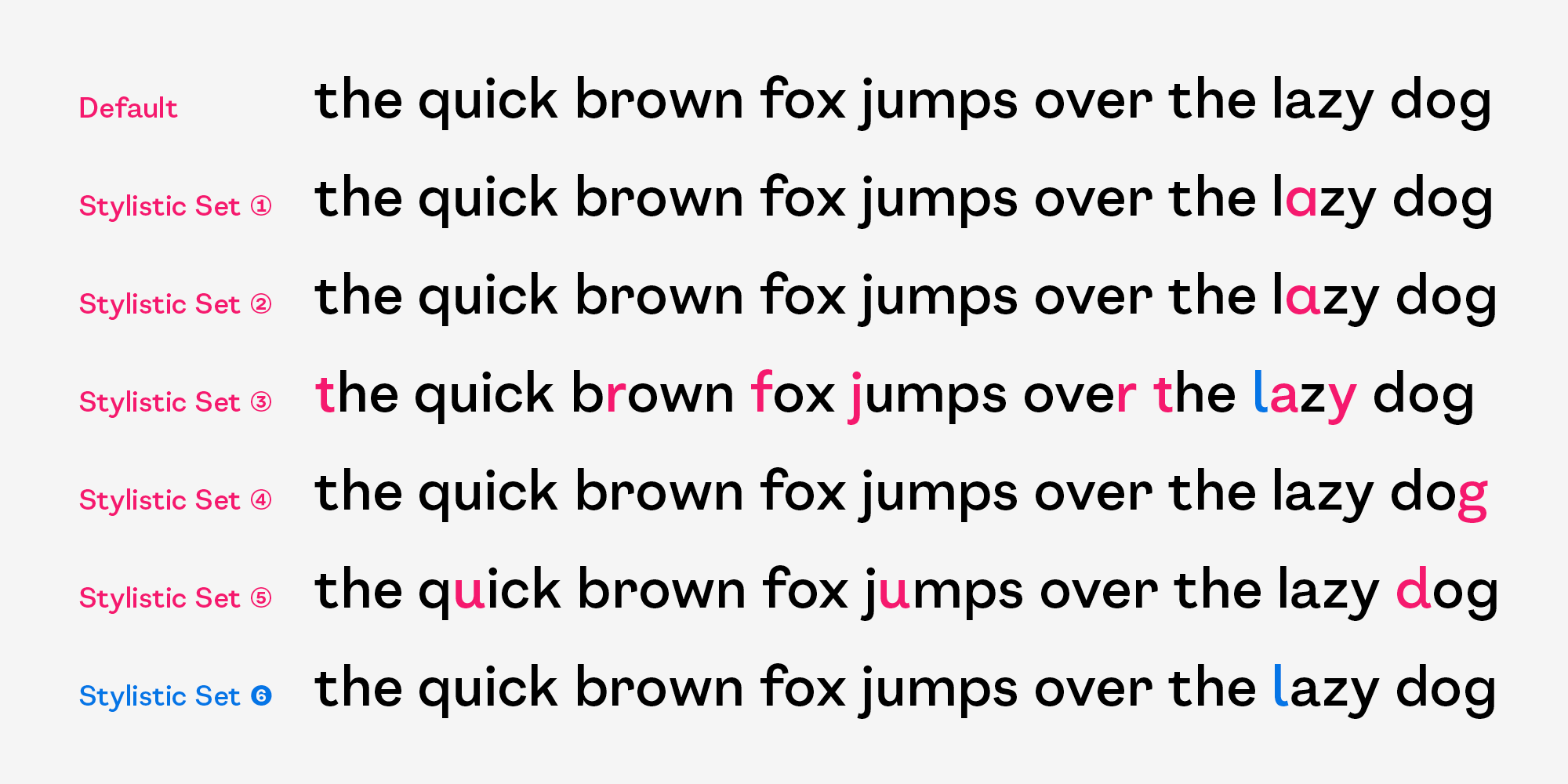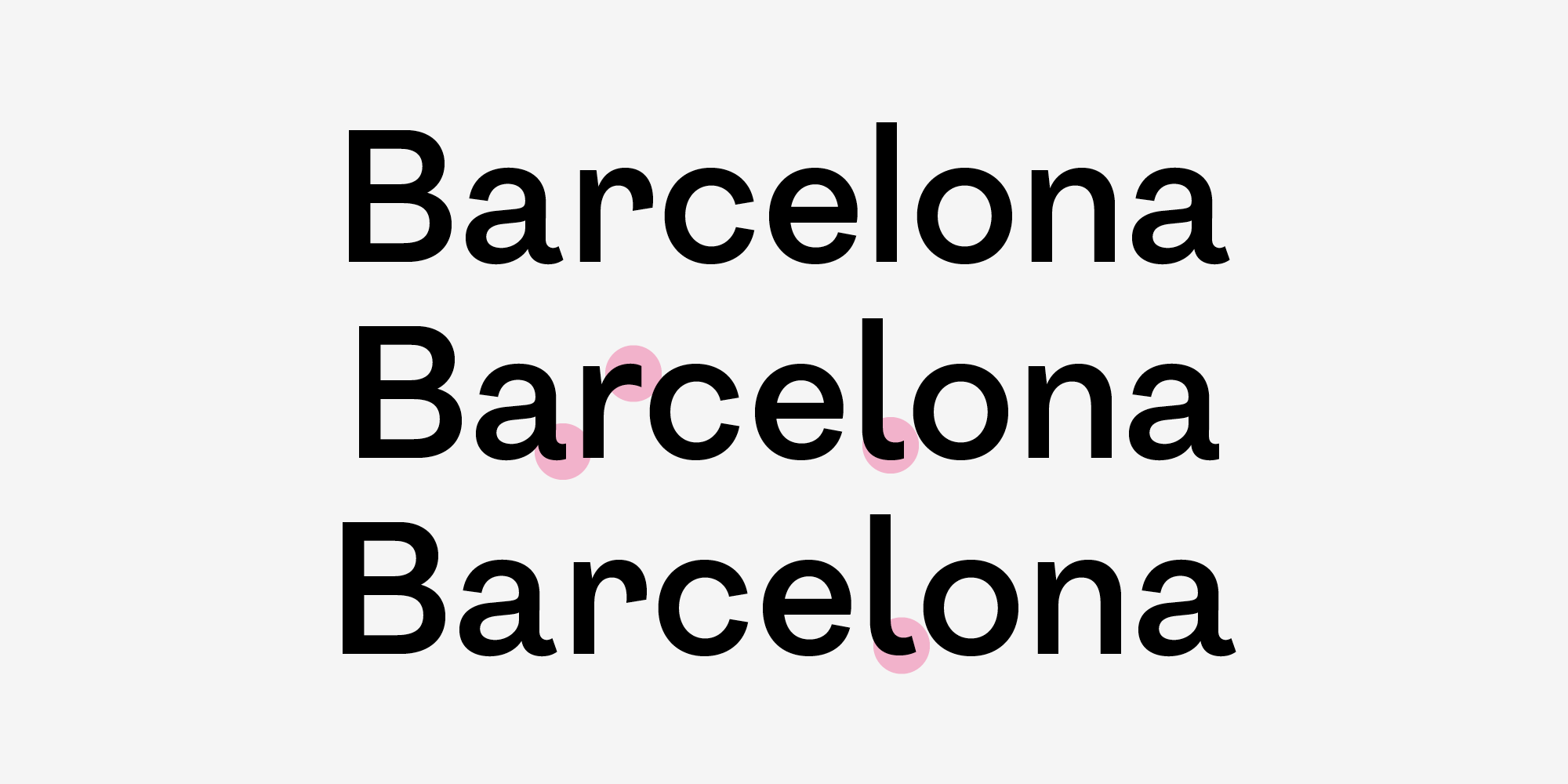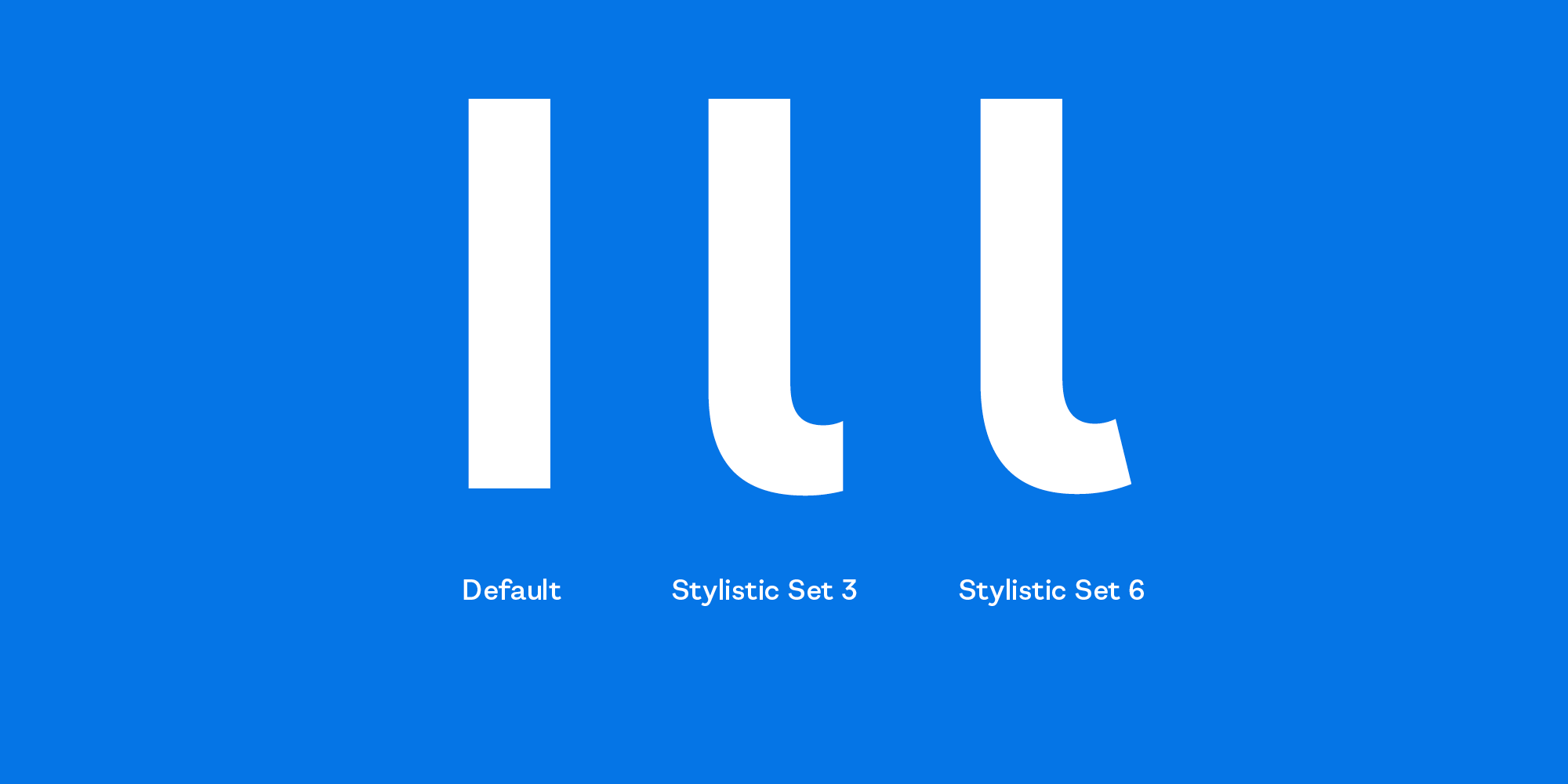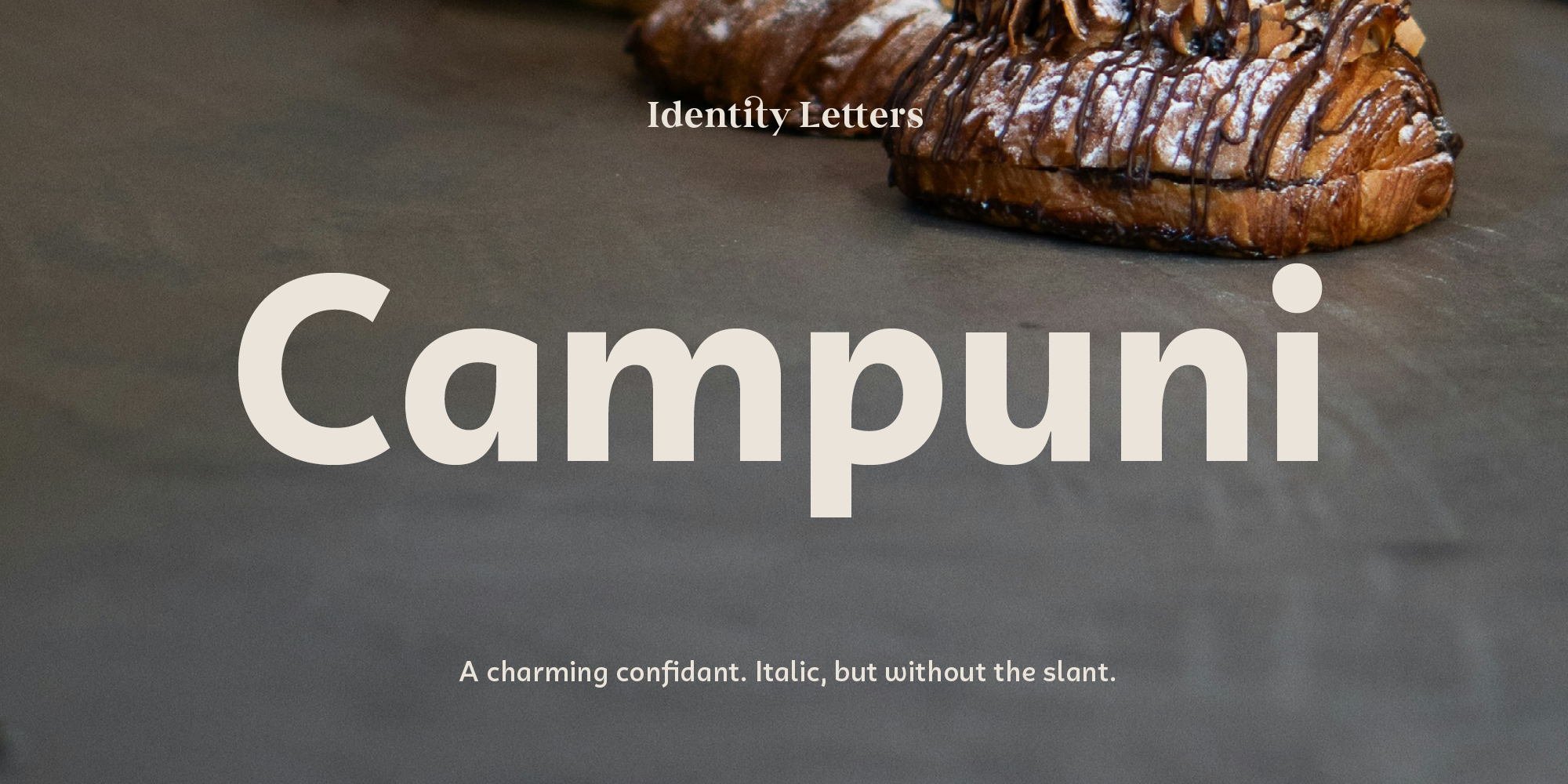
Zeichensequenz
Ich hätte sie gern so: AWyagqpdböiIl1306rnm.,; ß ẞB
Forensoftware (?) hat Minuskel-ß in Versal-ẞ geändert.
Hat das l jetzt ein Häkchen? Falls ja, habe ich es noch nicht entdeckt …
Gibt es ein Update für Kunden, die vor dem zusätzlichen Häkchen zugeschlagen haben? ;-)
Ich habe meine Schrift Campuni geupdated und Retalics (rechtsgeneigte Obliques) hinzugefügt. Außerdem gibt es mit Campuni Smile eine Stilvariante. Die Schrift gibt es mit dem Coupon „CampuniRetalic“ zurzeit 30% günstiger. Der Coupon ist bis zum 8. August gültig.
Campuni Retalic
Nice! Habe diese Art von Font jetzt öfter mal wieder bei neuen Sachen entdeckt. Vielleicht erlebt dieser Stil gerade wieder ein Revival?